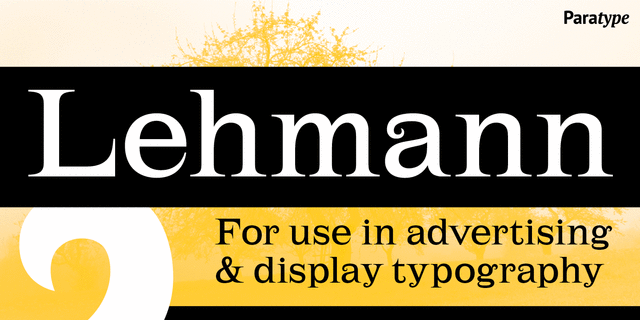
ПТ Леман™ Шрифт разработан по мотивам рисунков гарнитуры Широкий Ренессанс и других шрифтов акционерного общества «Словолитни О.И.Лемана» (С.-Петербург, ок. 1874) для фирмы ParaType в 2001 году (дизайнер Тагир Сафаев). Шрифт так называемого эльзевировского типа, с тонкими треугольными засечками и острыми спиралевидными концевыми элементами. Предназначен для набора акцидентной и рекламной продукции.